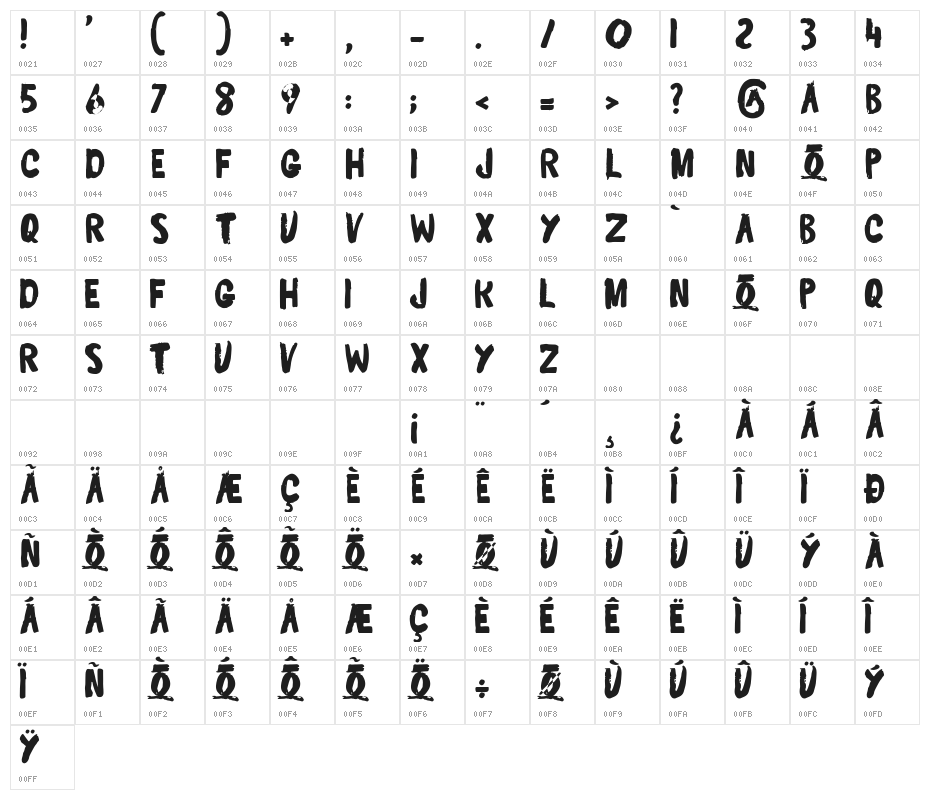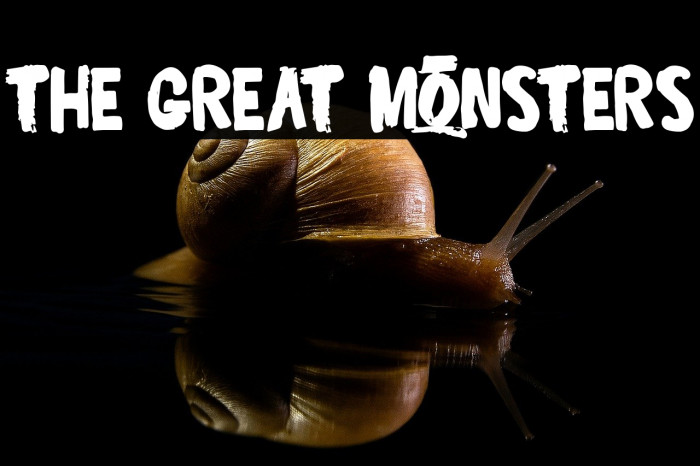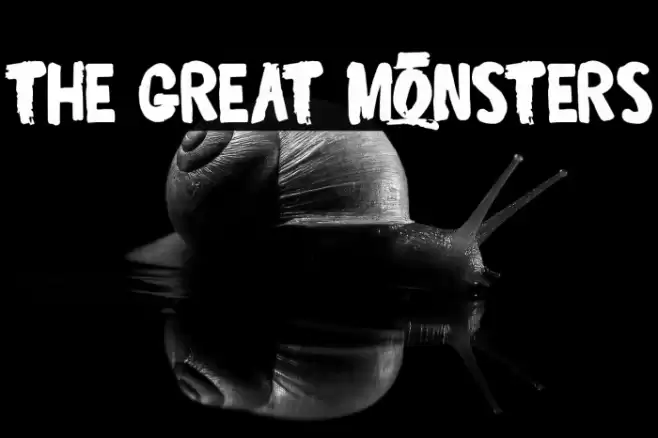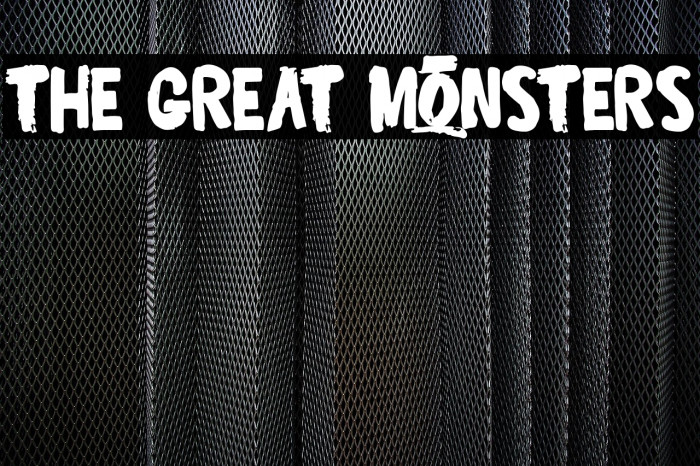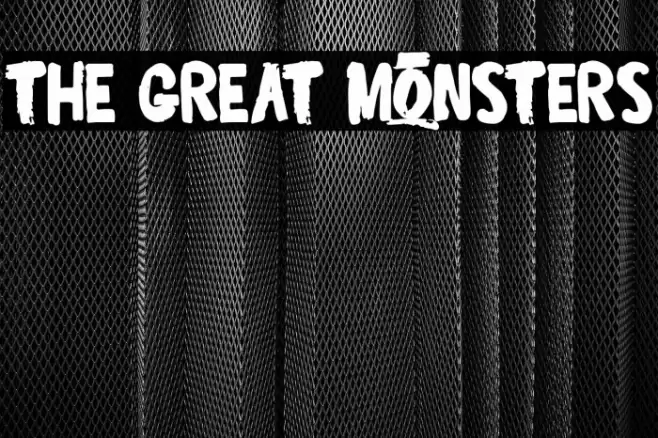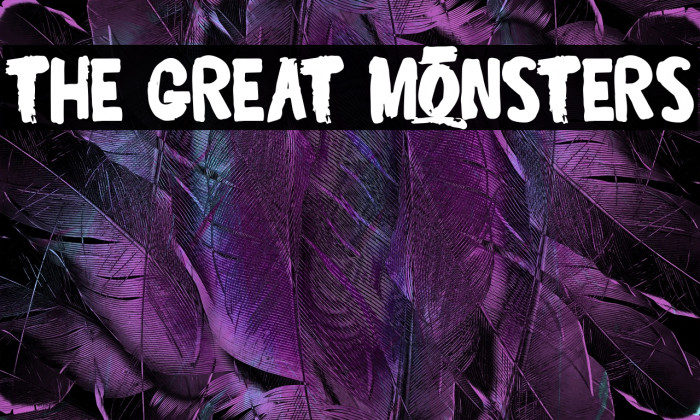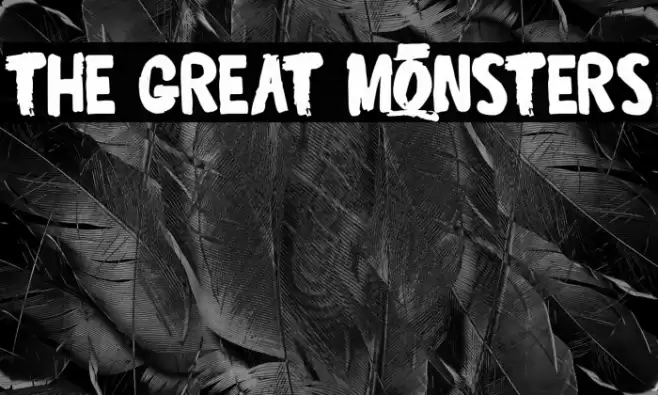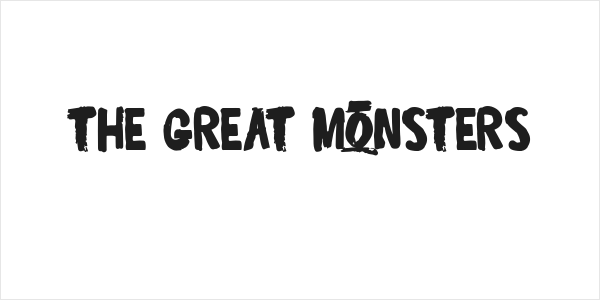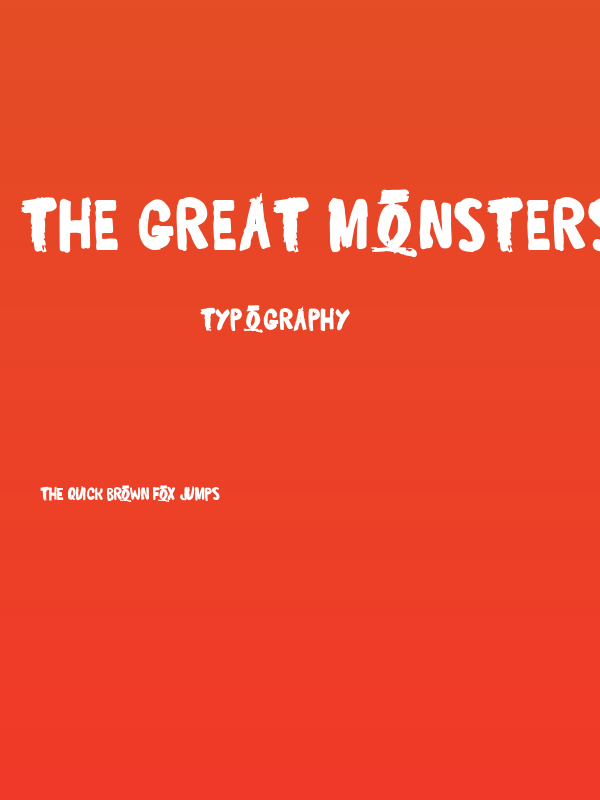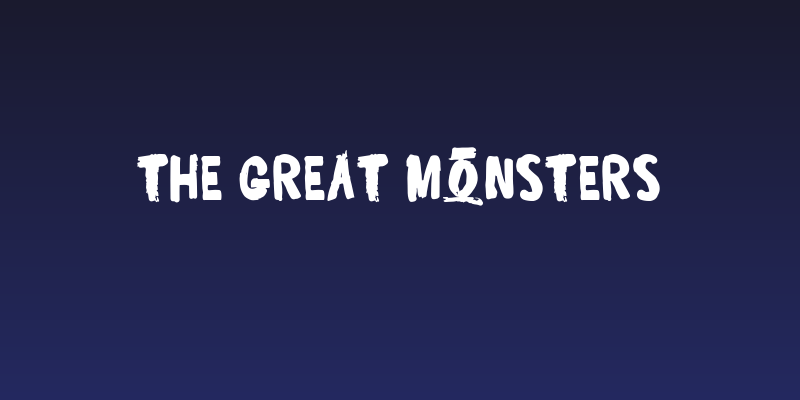
The Great Monsters Font
| समग्र शैली | Decorative |
| उपयोग का मामला | Headlines, Logos, Posters |
| सुझाए गए प्रोजेक्ट | Ideal for poster designs, album covers, branding for edgy or artistic products, and any project needing a bold, artistic touch. |